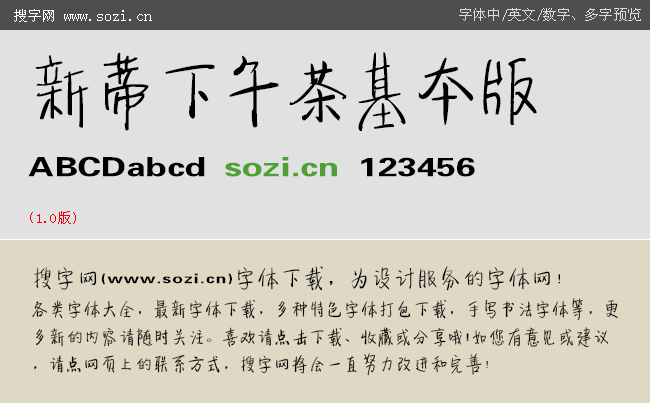
新蒂下午茶基本版字體
搜字網(wǎng)給大家提供一款書(shū)法風(fēng)格的字體新蒂下午茶字體下載。新蒂下午茶字體是一款手寫(xiě)風(fēng)格的中文簡(jiǎn)體字體,非常有手寫(xiě)感,廣泛應(yīng)用于簽名、藝術(shù)設(shè)計(jì)、創(chuàng)意廣告等行業(yè),喜歡的用戶可下載收藏。